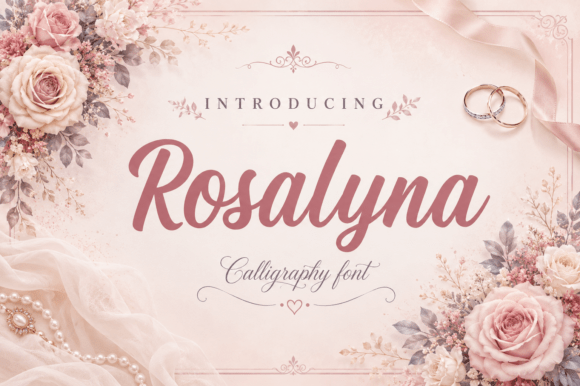
Rosalyna
หากคุณกำลังมองหาเนื้อหาคุณภาพสูงเช่น Rosalyna แพ็คเกจพรีเมียมนี้เป็นตัวเลือกที่ยอดเยี่ยมสำหรับโปรเจ็กต์สร้างสรรค์ของคุณ
ไม่ว่าคุณจะสร้างผลิตภัณฑ์ POD (Print on Demand) คำเชิญงานแต่งงาน หรือกราฟิกโซเชียลมีเดีย Rosalyna ก็เหมาะสมอย่างยิ่ง